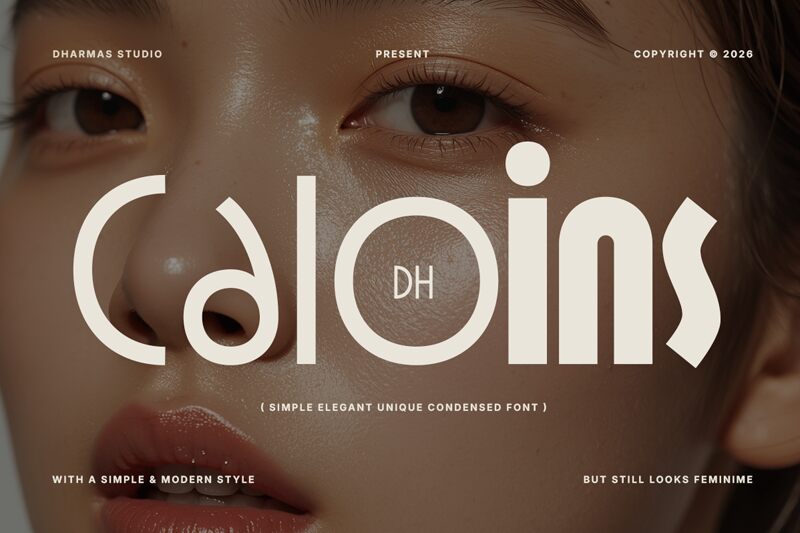
Dh Caloins DEMO Extra Bold
Dh Caloins de Dharmas Studio es una tipografía retro de estilo display gratuita con formas redondeadas y casi geométricas, que ofrece un ritmo compacto y suave. Sus trazos parecen más construidos que caligráficos, destacando por curvas fluidas, cortes sencillos y un detalle circular distintivo que dota a la familia de un carácter inspirado en la rotulación manual.
Dh Caloins funciona de maravilla en logotipos, titulares de carteles, packaging, portadas de álbumes y gráficos para redes sociales donde una tipografía con fuerza puede sostener el diseño. Esta fuente gratuita también es ideal para señalización breve y branding de eventos, ya que sus formas sólidas y sus curvas inusuales crean un punto de enfoque claro sin necesidad de adornos extra.